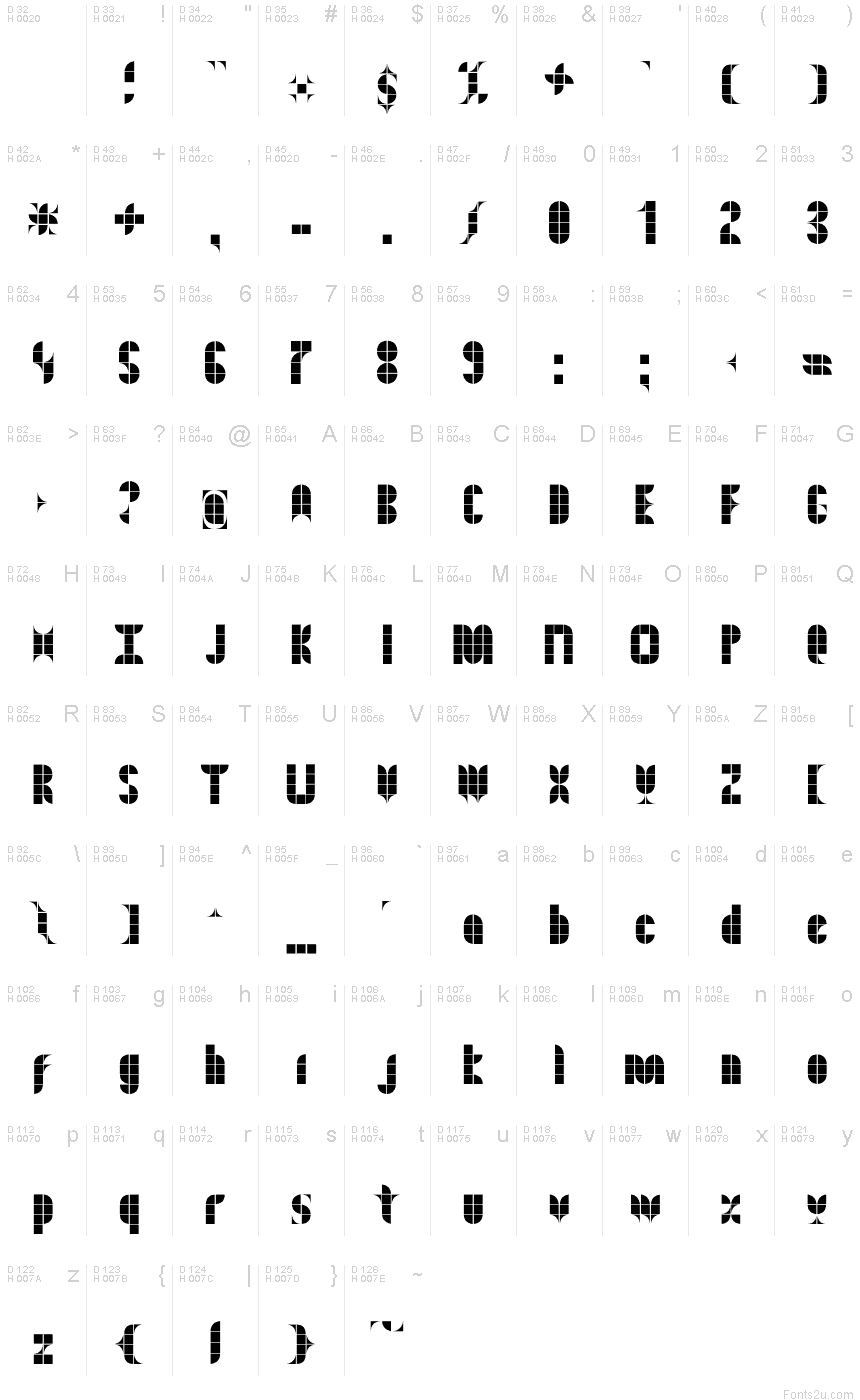
Kitchen Tiles od Lisa D. Jenkins to bezpłatny techno-displayowy krój pisma, który zamienia każde słowo w kafelkową mozaikę. Każda litera zbudowana jest z błyszczących, kwadratowych modułów, przedzielonych cienkimi białymi liniami fug, dzięki czemu tekst przypomina futurystyczną ścianę z ceramicznych płytek. Gładkie krzywe spotykające się ze sztywnymi liniami siatki tworzą śmiały, architektoniczny rytm, który kojarzy się zarówno z panelem retro komputera, jak i elegancką glazurą kuchenną.
Dzięki Kitchen Tiles Twoje nagłówki zyskują natychmiast konstrukcję i niemal namacalny charakter, który przyciąga wzrok zarówno na ekranie, jak i w druku. Ten darmowy font świetnie sprawdza się na plakatach sci-fi, okładkach muzyki elektronicznej, odważnych projektach opakowań, ulotkach eventowych, logotypach oraz wyrazistych grafikach do mediów społecznościowych, gdzie zależy Ci na mocnym, graficznym wzorze wtopionym w same litery. Użyj go w dużym rozmiarze, aby wyeksponować strukturę płytek, a jako tekst uzupełniający dobierz czysty, neutralny bezszeryfowy krój, aby uwaga skupiała się na jego geometrycznej fakturze.